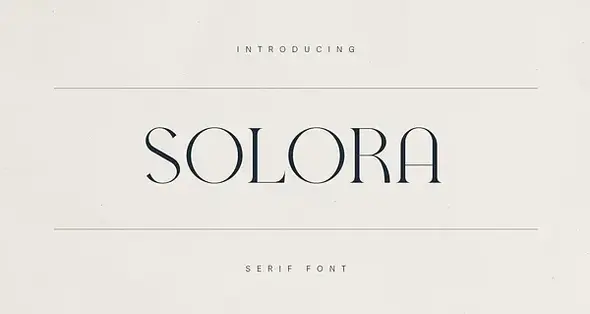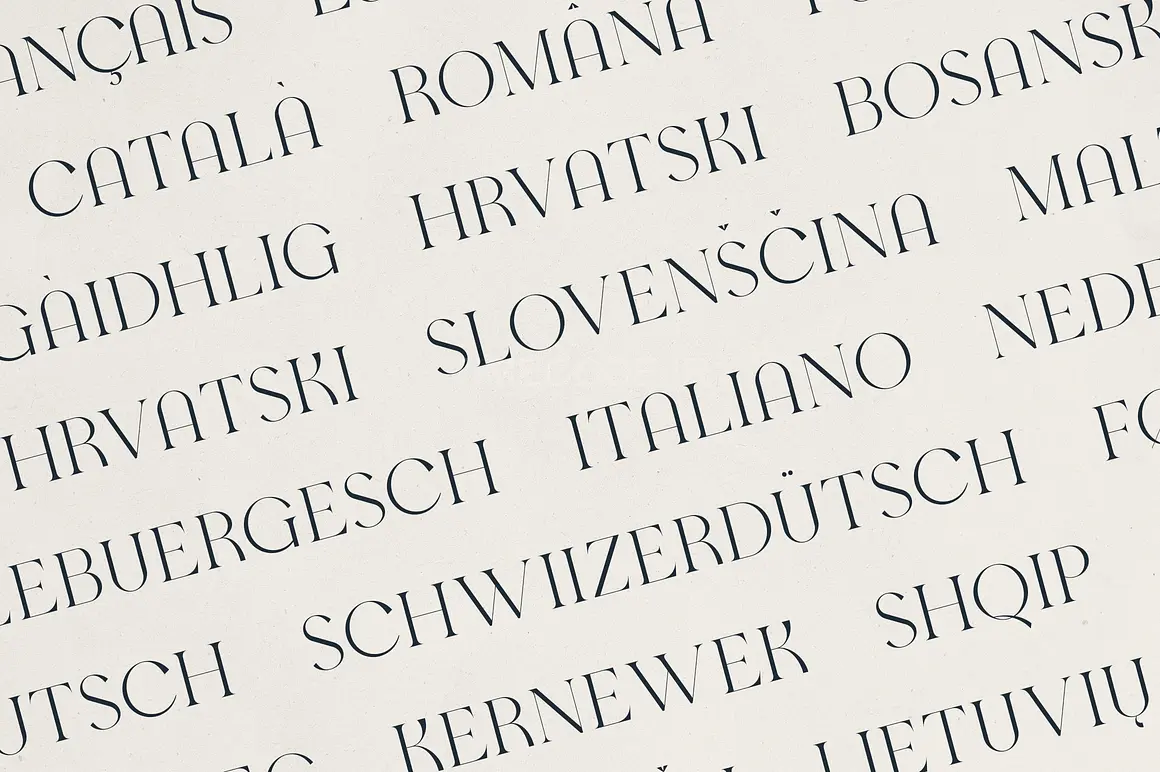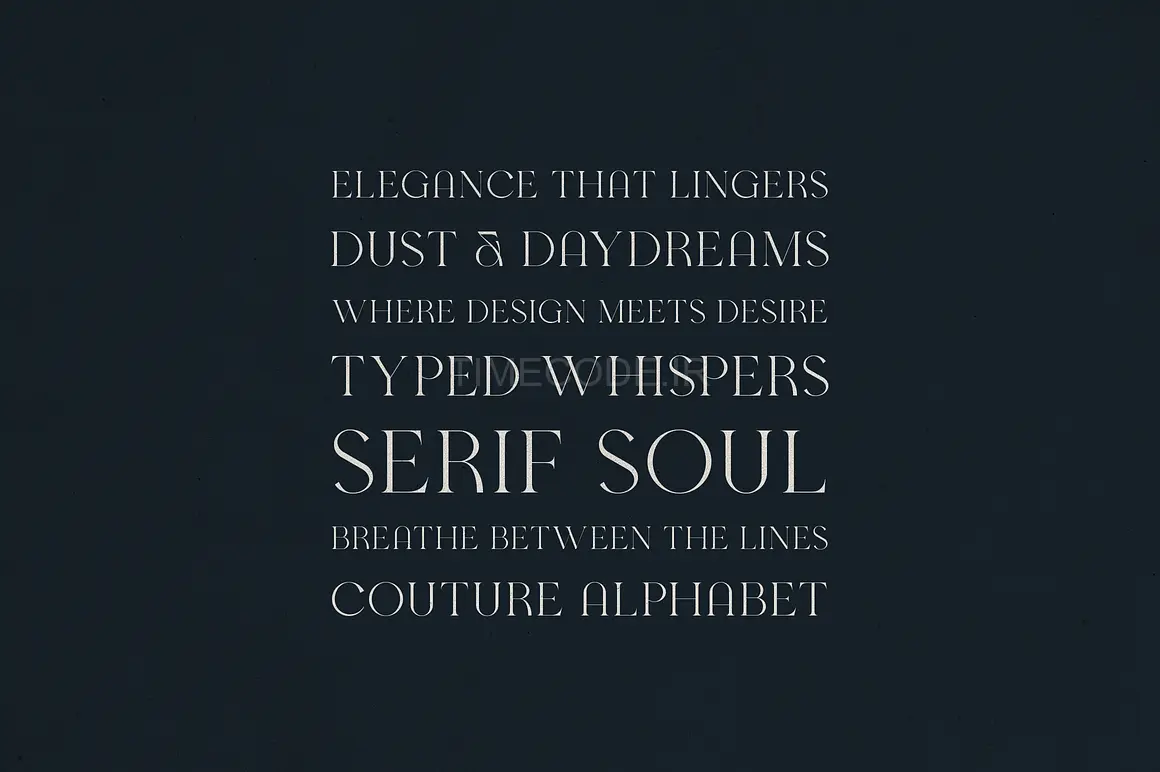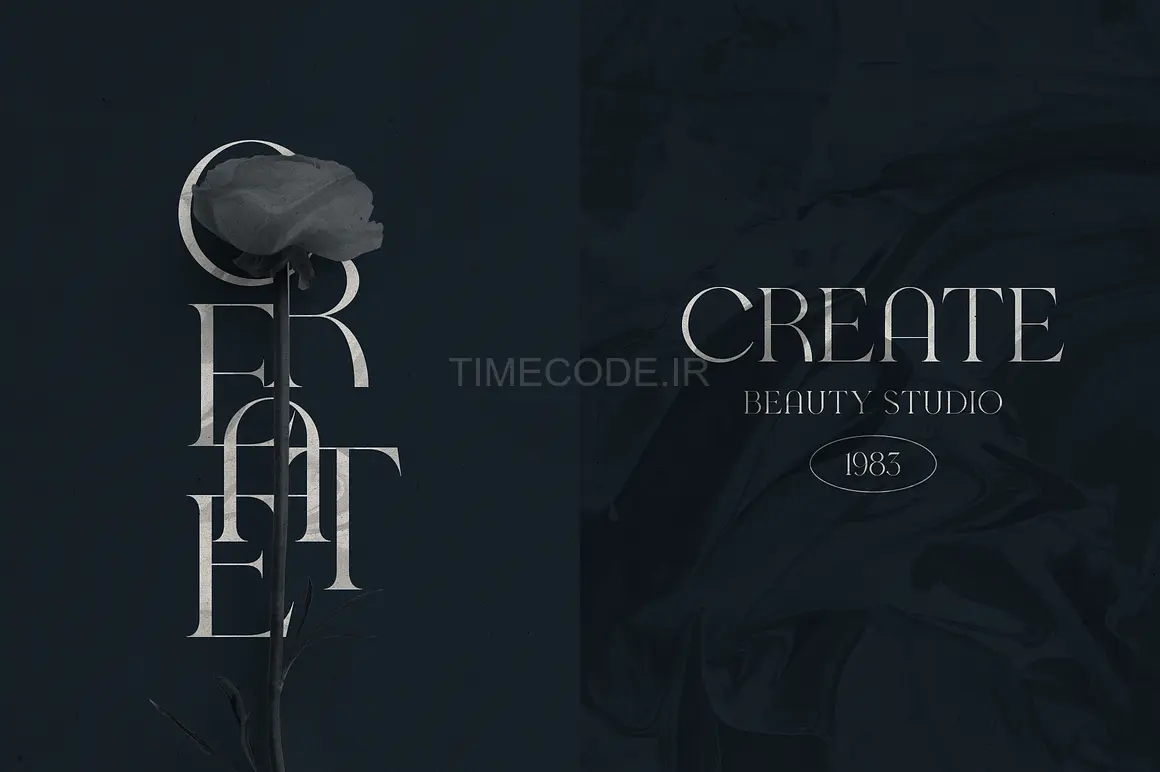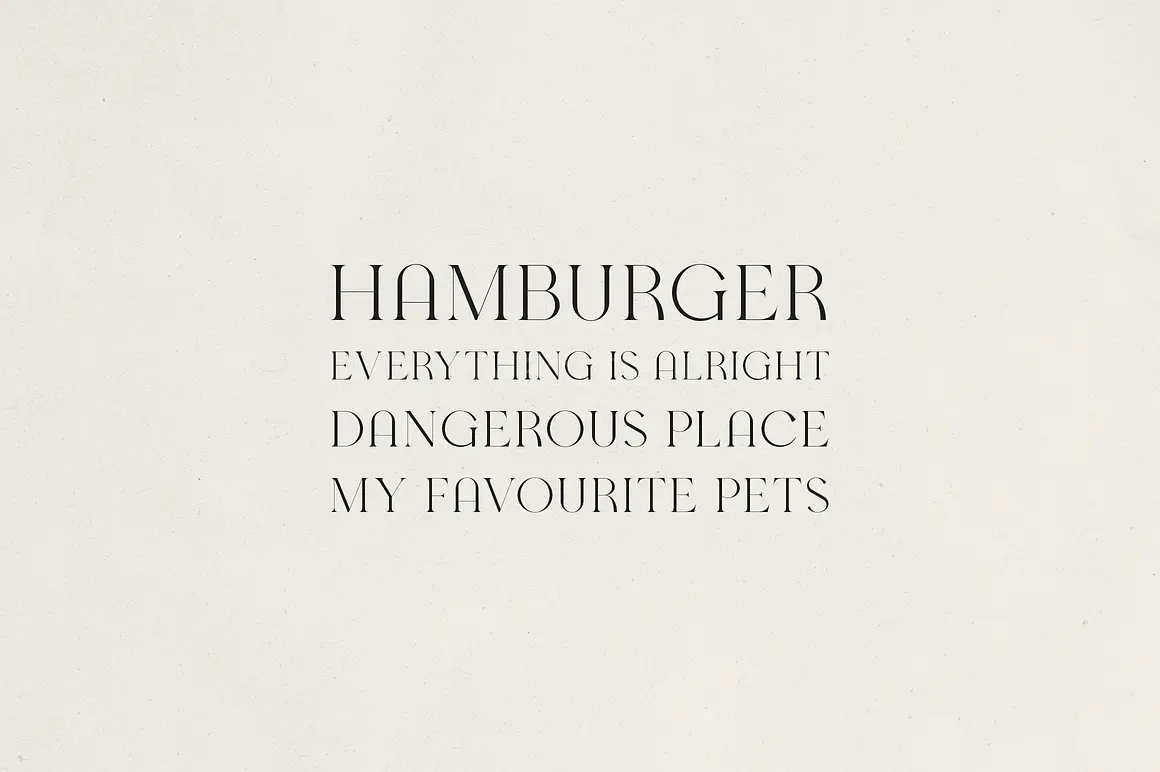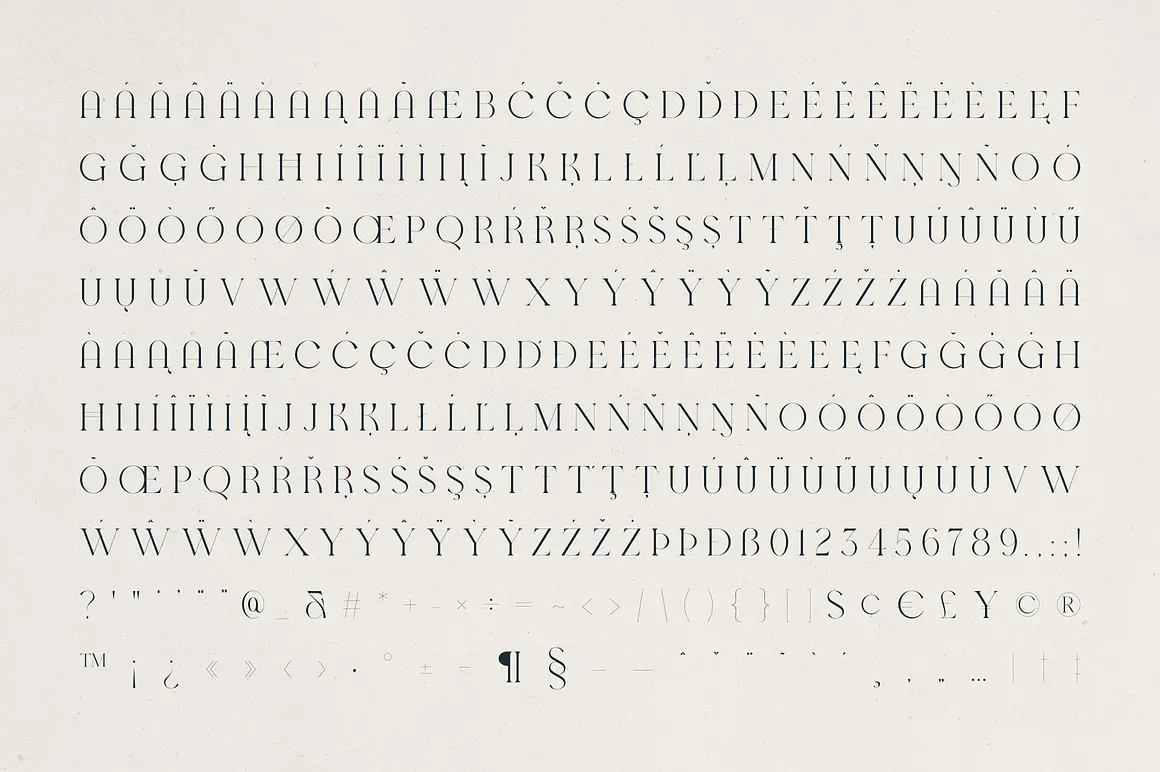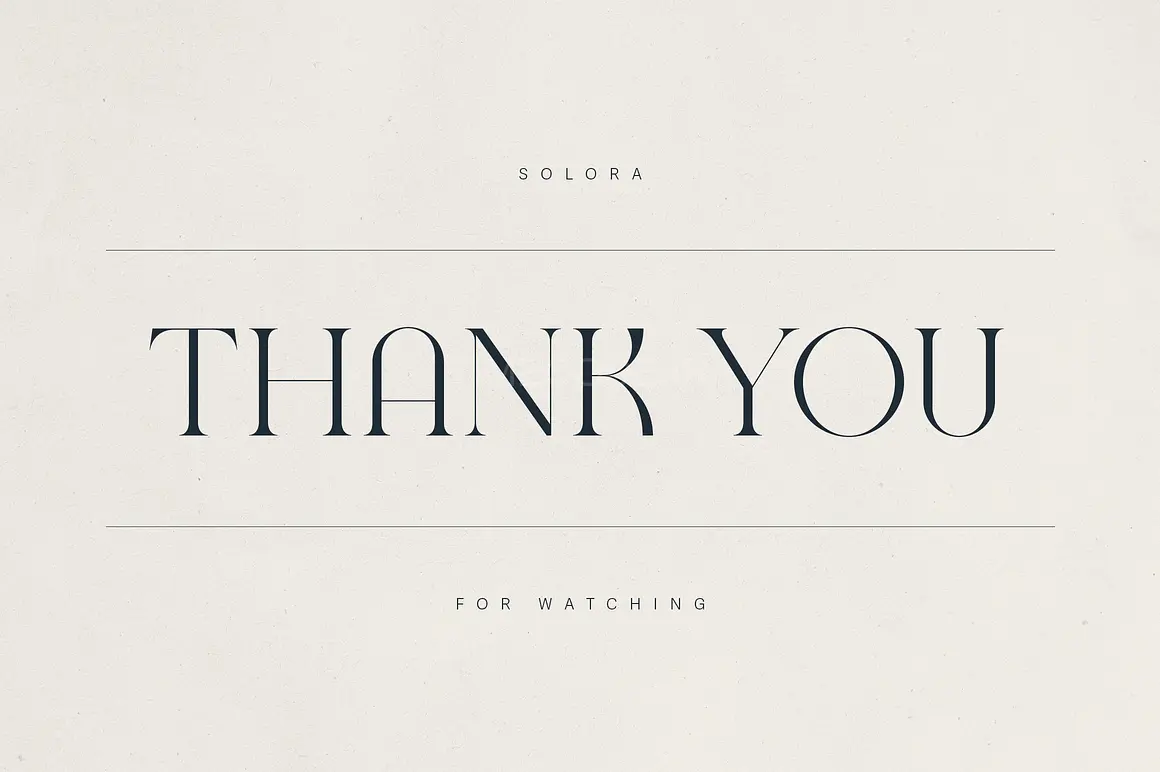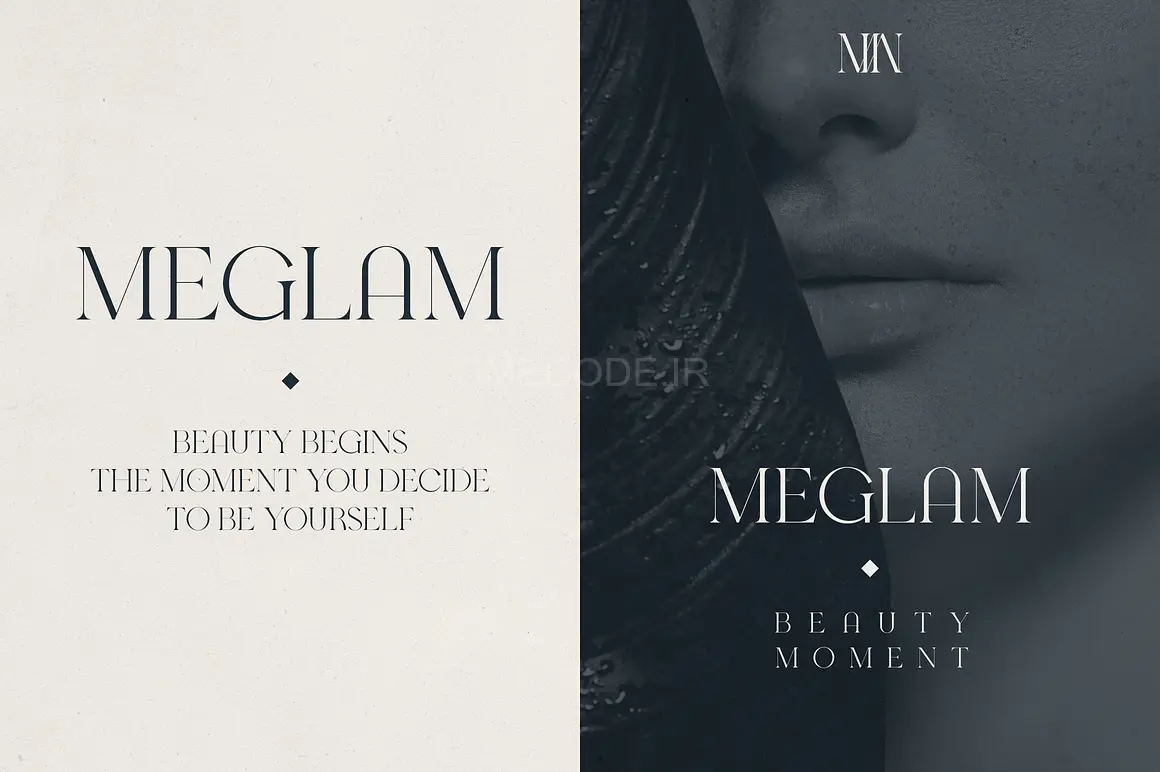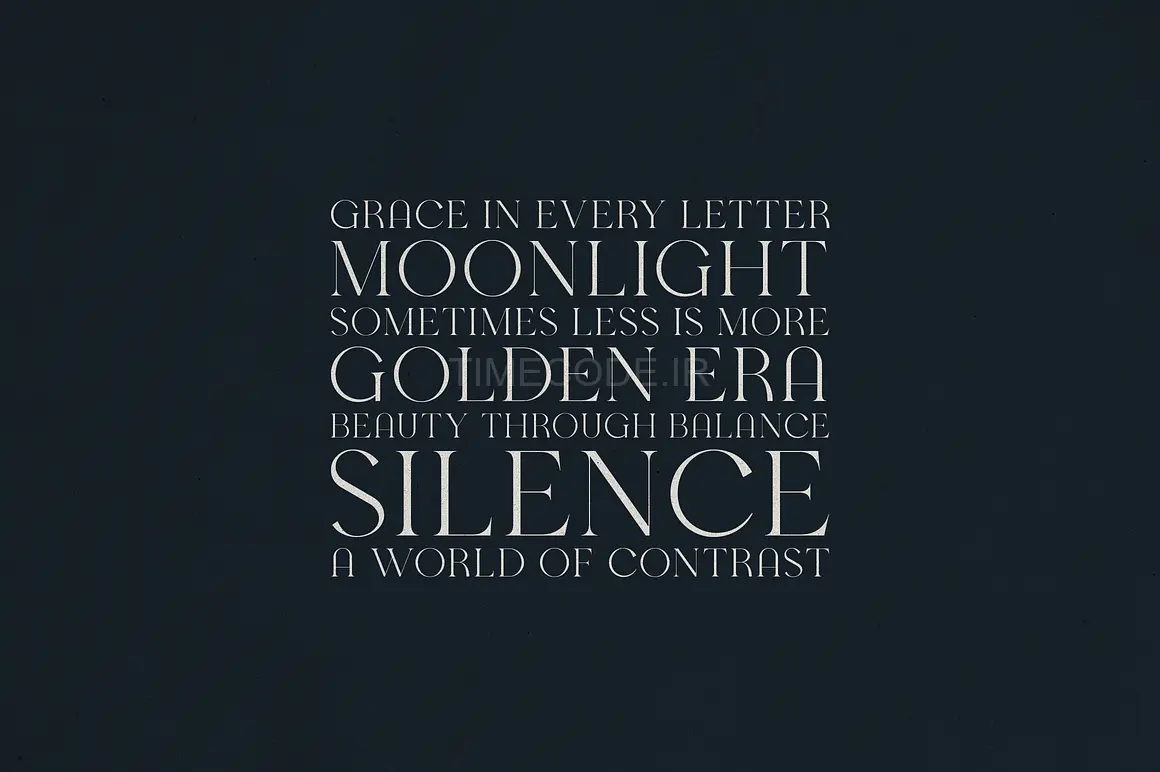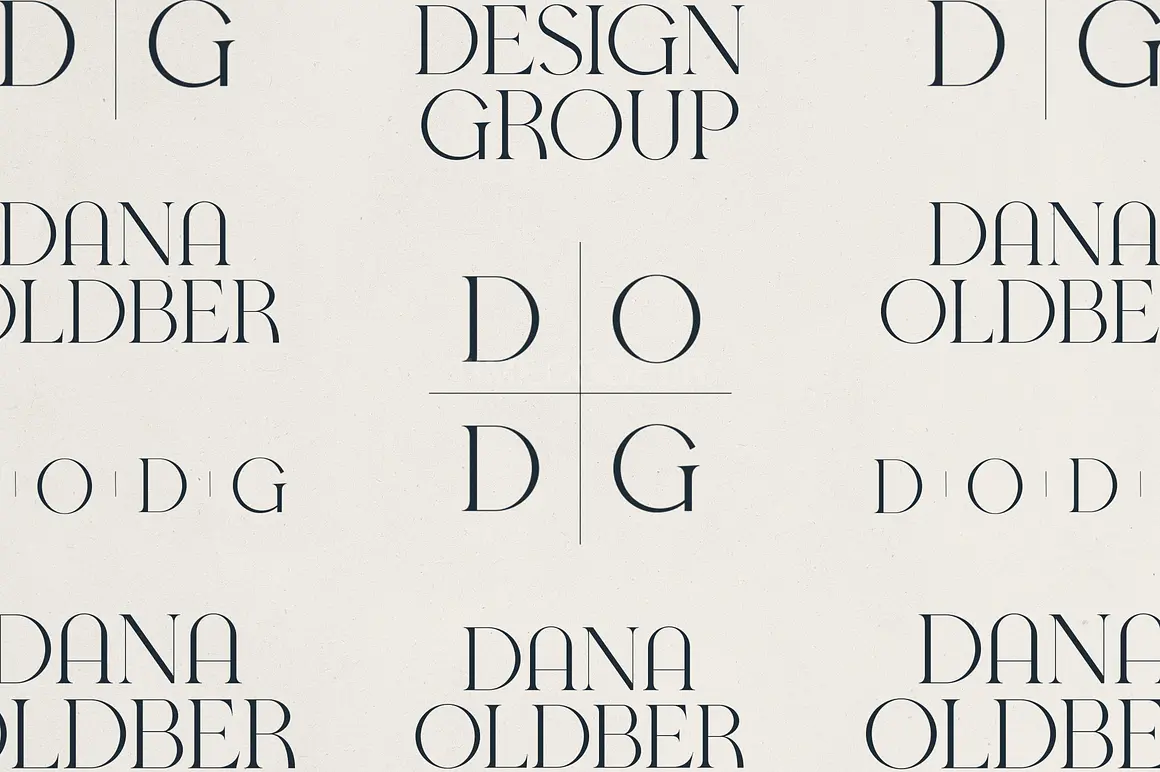
فونت انگلیسی سریف شیک و مدرن
Solora یک فونت سریف بی‌زمان و ظریف که طراحی شده تا پیچیدگی و سبک را به هر پروژه‌ای بیاورد. با ضربه‌های پرکنتراست، منحنی‌های زیبا، و فرم‌های حروف الهام‌گرفته از مد روز، Solora برای طراحانی که به دنبال یک تایپ‌فیس تصفیه‌شده با پیچ و تاب مدرن هستند، بی‌نقص است.
Solora با توجه به جزئیات ساخته شده، سریف‌های شیک و نسبت‌های بلند آن، اعتماد به نفس و تجمل را به نمایش می‌گذارند – و آن را به انتخابی ایده‌آل برای برندسازی، طرح‌بندی‌های سرمقاله‌ای، طراحی بسته‌بندی، کمپین‌های مد، و تبلیغات زیبایی سطح بالا تبدیل می‌کند.
چه در حال ایجاد یک لوگوی لوکس، یک صفحه مجله شیک، یا یک دعوتنامه جذاب باشید، Solora فوراً ظرافت و لمسی از درام را اضافه می‌کند. ساختار همه‌کاره آن اجازه می‌دهد تا هم در سرفصل‌ها و هم در متن‌های بدنه تصفیه‌شده بدرخشد.
ویژگی‌های فونت:
• سبک سریف ظریف و مدرن
• ضربه‌های پرکنتراست برای تأثیرگذاری دراماتیک
• منحنی‌های نرم و سریف‌های تیز
• ایده‌آل برای برندسازی لوکس و طراحی‌های سرمقاله‌ای
• عالی برای لوگوها، مجلات، بسته‌بندی و دعوتنامه‌ها
• پشتیبانی از ۸۵ زبان
مناسب برای:
• برندسازی مد و زیبایی
• طراحی سرمقاله و مجله
• دعوتنامه‌های عروسی و لوکس
• گرافیک رسانه‌های اجتماعی
• بسته‌بندی مینیمالیستی
• لوگوها و سرفصل‌های سطح بالا
Solora – Elegant Modern Serif Font
Introducing Solora, a timeless and elegant serif font designed to bring sophistication and style to any project. With its high-contrast strokes, graceful curves, and couture-inspired letterforms, Solora is perfect for designers seeking a refined typeface with a modern twist.
Crafted with attention to detail, Solora’s sleek serifs and tall proportions exude confidence and luxury—making it the ideal choice for branding, editorial layouts, packaging design, fashion campaigns, and high-end beauty promotions.
Whether you're creating a luxury logo, stylish magazine spread, or a chic invitation, Solora adds instant elegance and a touch of drama. Its versatile structure allows it to shine in both headlines and refined body text.
Font Features:
- Elegant, modern serif style
- High-contrast strokes for dramatic impact
- Smooth curves and sharp serifs
- Perfect for luxury branding & editorial design
- Great for logos, magazines, packaging & invitations
- Supports 85 languages
Perfect For:
- Fashion & beauty branding
- Editorial & magazine design
- Wedding & luxury invitations
- Social media graphics
- Minimalist packaging
- High-end logos & headlines